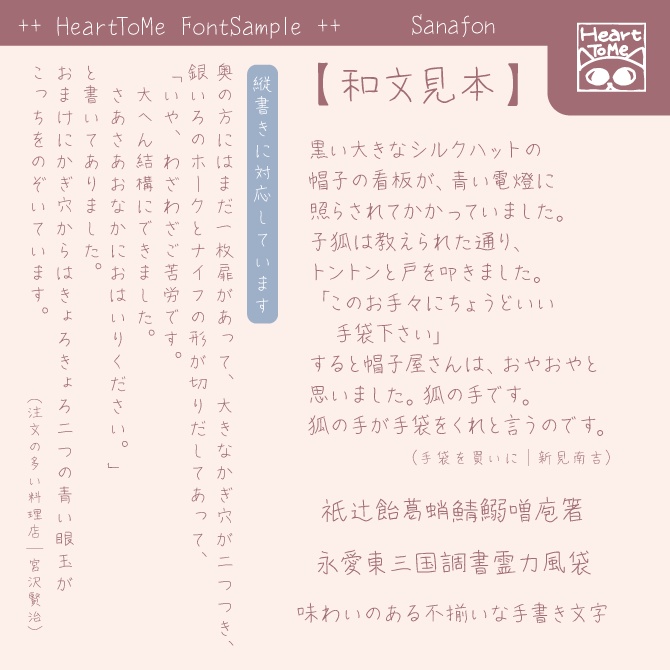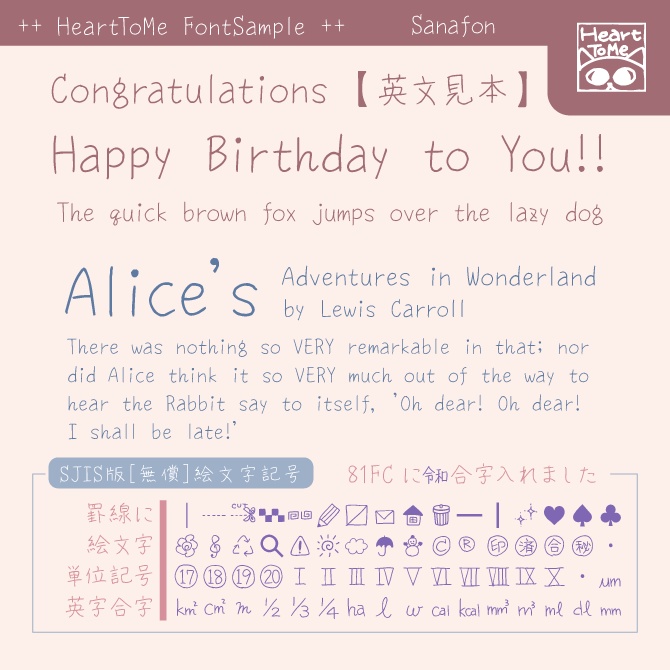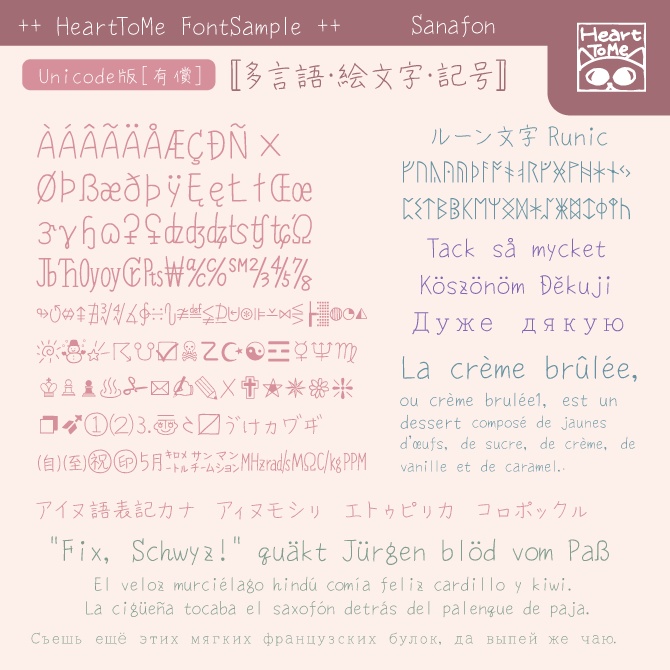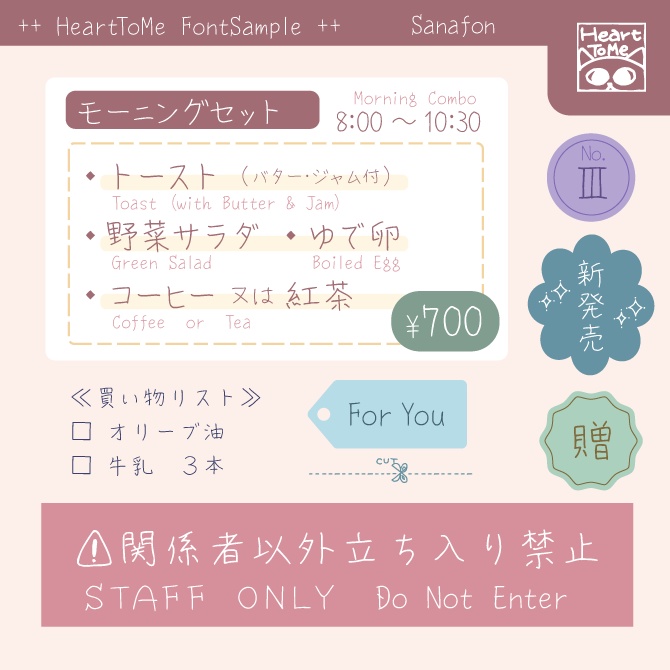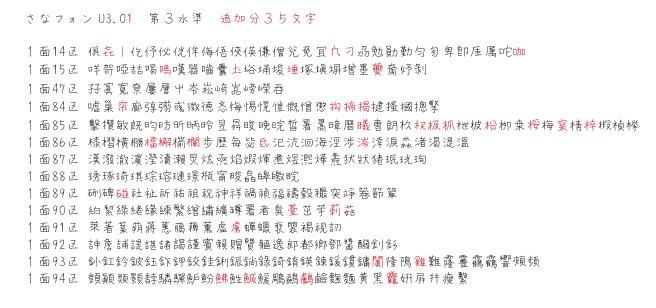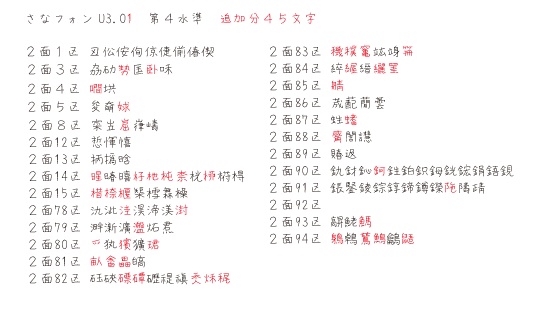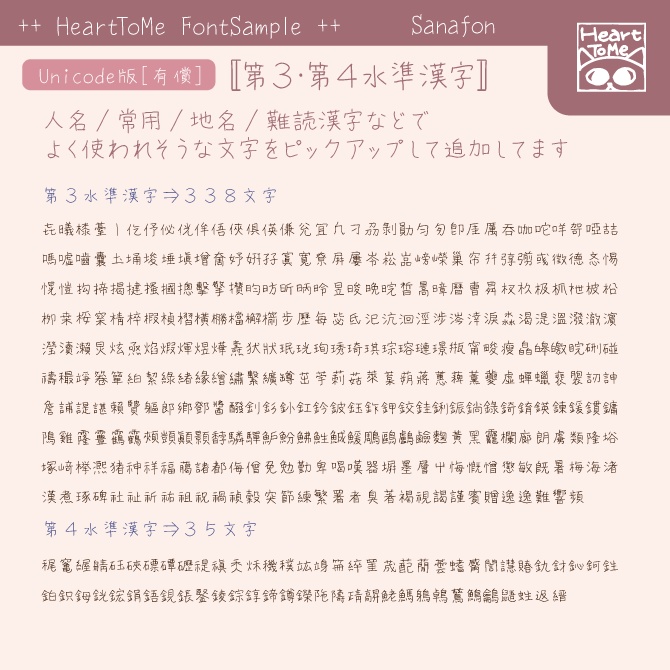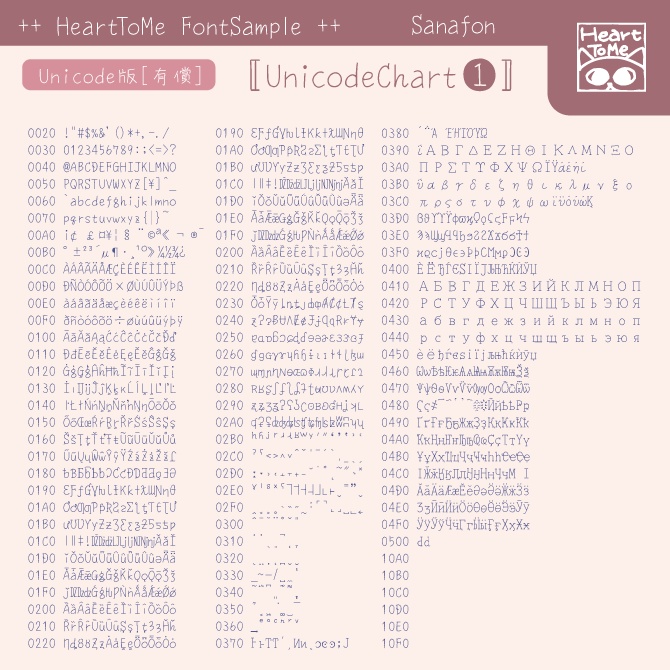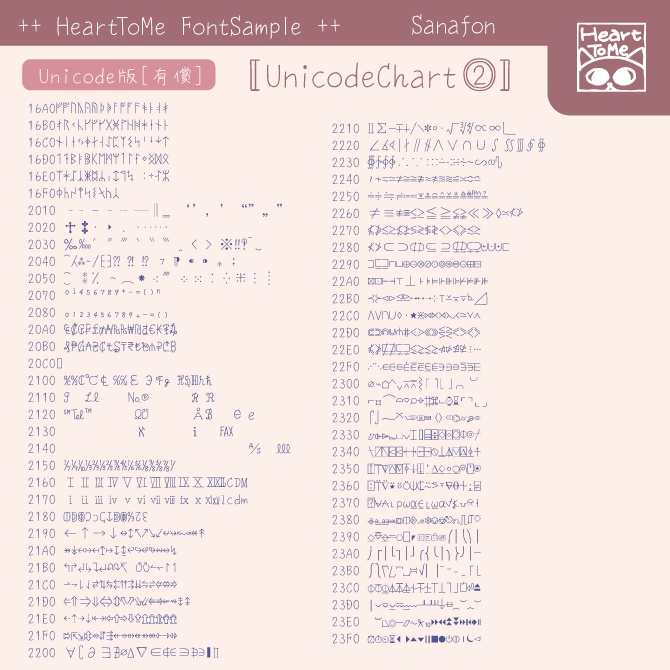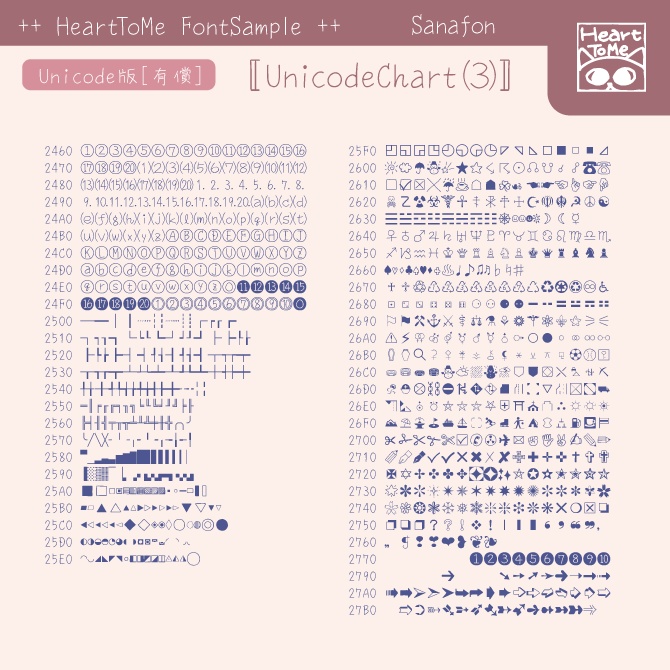
さなフォン(手書き和文フォント) 無償/有償
ちょっと細めの、サインペンとかボールペンで書いたような感じの書体 楷書とまではいかないけど、あまり崩してはいません 一文字ずつ書いた「本物の手書き」ならではの不ぞろいな感じが特徴です ◆応援の投げ銭カンパ大歓迎です!投げ銭版・BOOSTしていただけると嬉しいです 無償条件での使用でも応援したい・Unicode版を使いたい方は 「有償投げ銭版」をご利用ください
Shift_JIS(JIS90字形) 文字コードWindows-31J(MS932)[最大7592文字] 半角かな・カナ・アルファベット ひらがな・カタカナ・アルファベット・ギリシャ・キリル・各種記号 第一水準漢字・第二水準漢字・IBM拡張文字 罫線の縦横一本線以外 → 絵文字 カナ単位合字 → 英字単位合字
Shift_JIS + Unicode基本多言語面(BMP)領域 ラテン拡張・ルーン文字、アイヌ語小カナ・記号・規定絵文字の他 一部区域にオリジナル絵文字・装飾など多数収録 JIS第3・第4水準漢字から 人名・常用・地名・難読漢字などを収録 ※サンプル画像に一部リストを載せているので参考にしてください